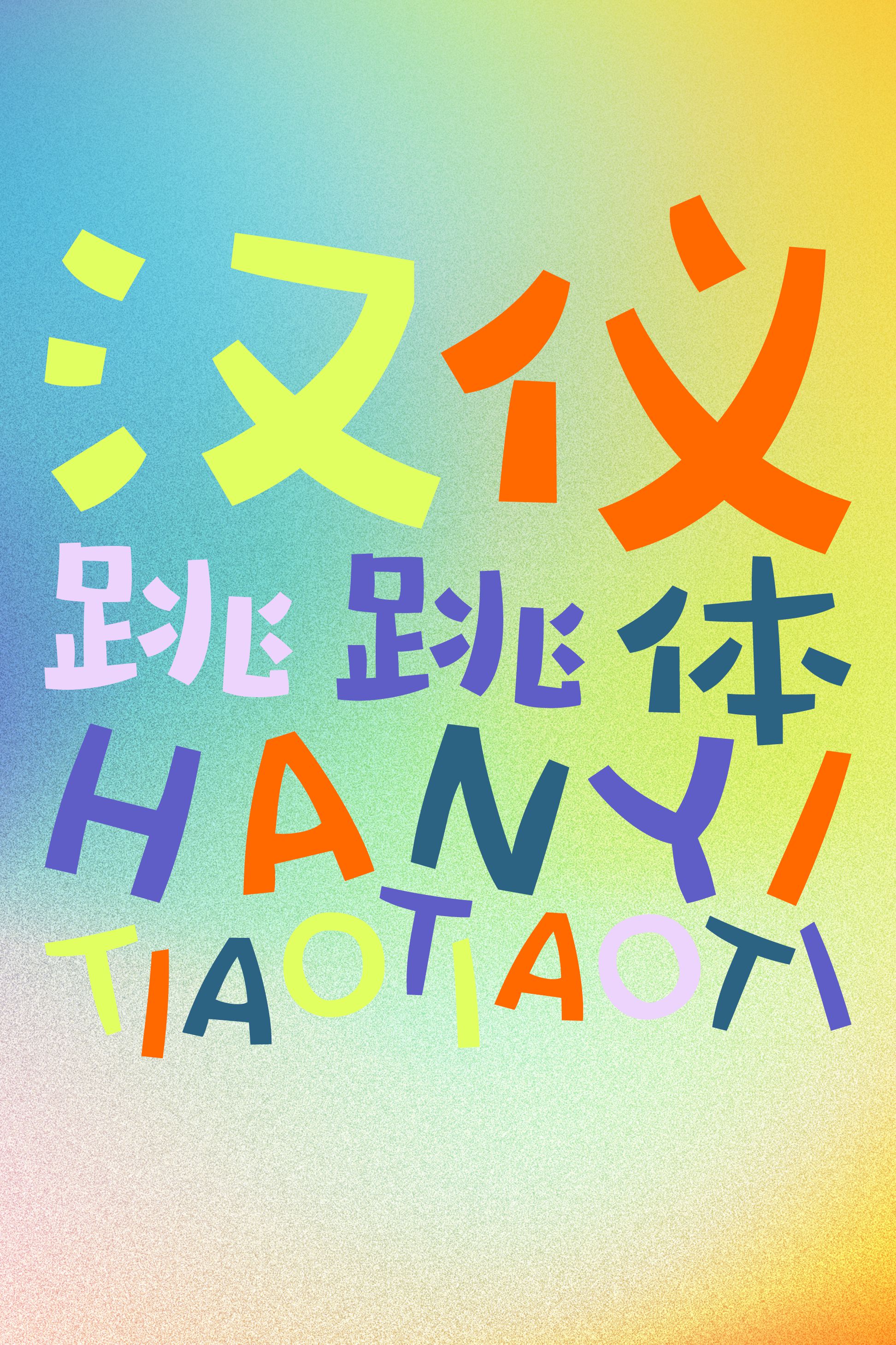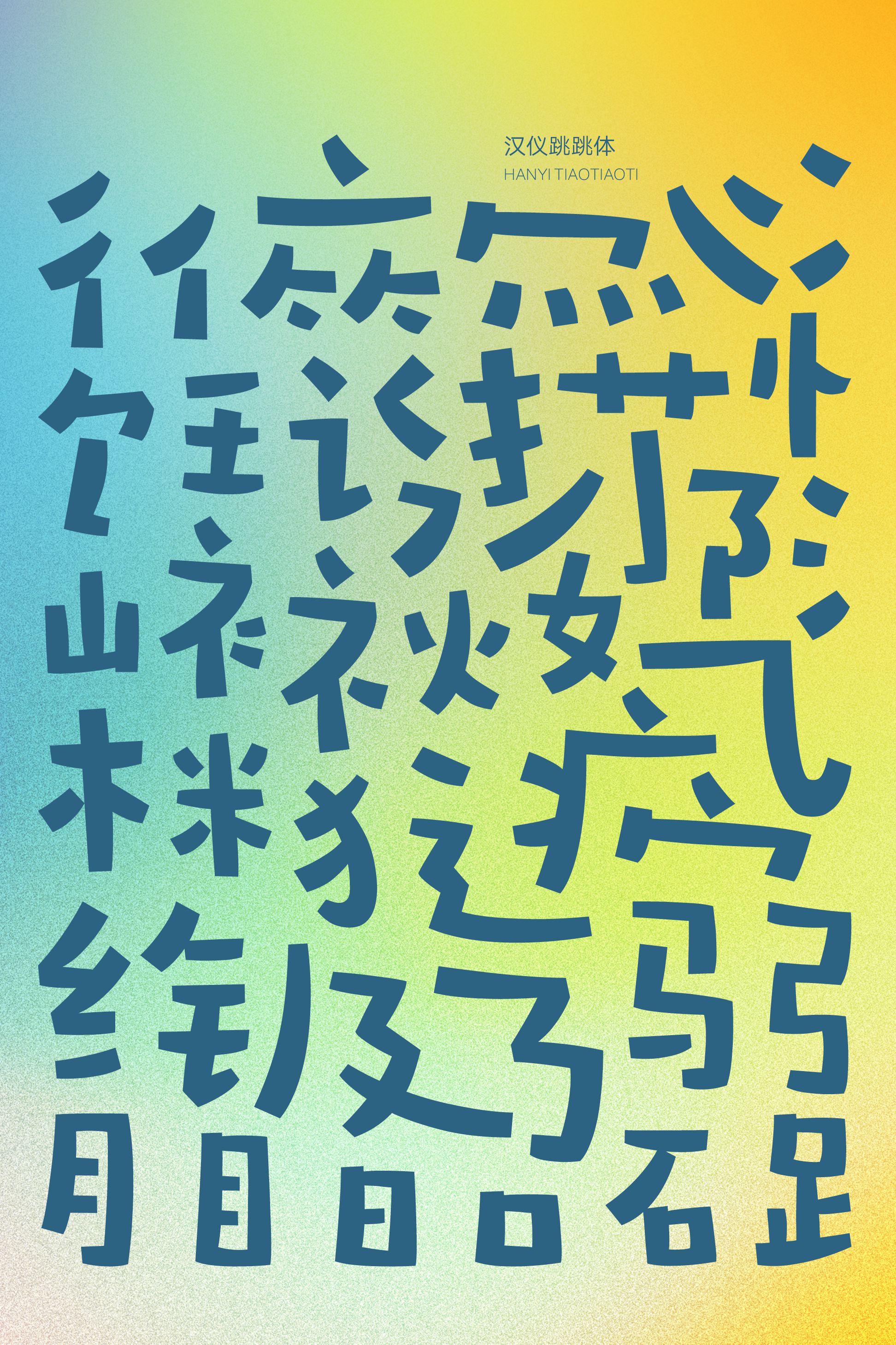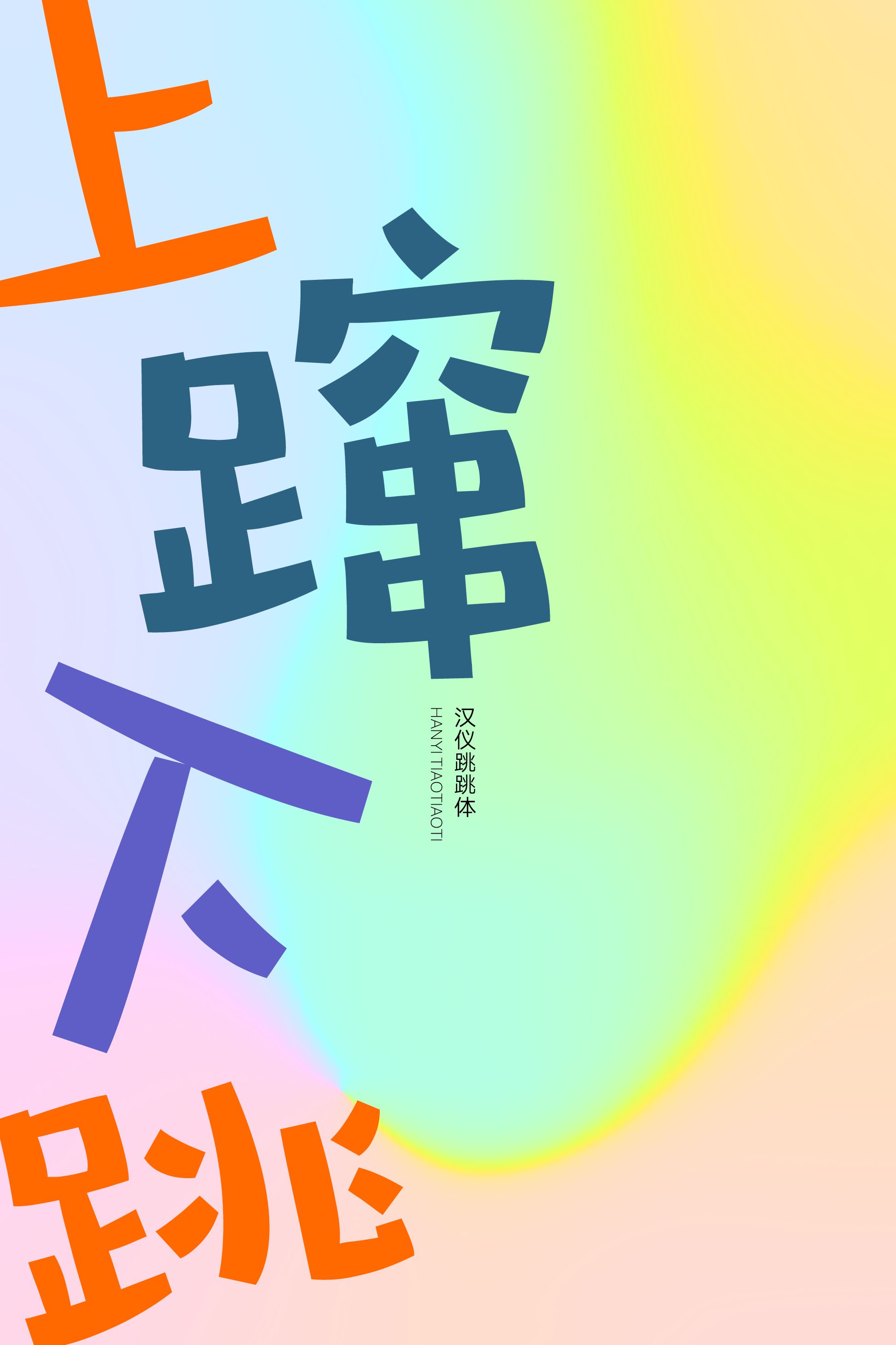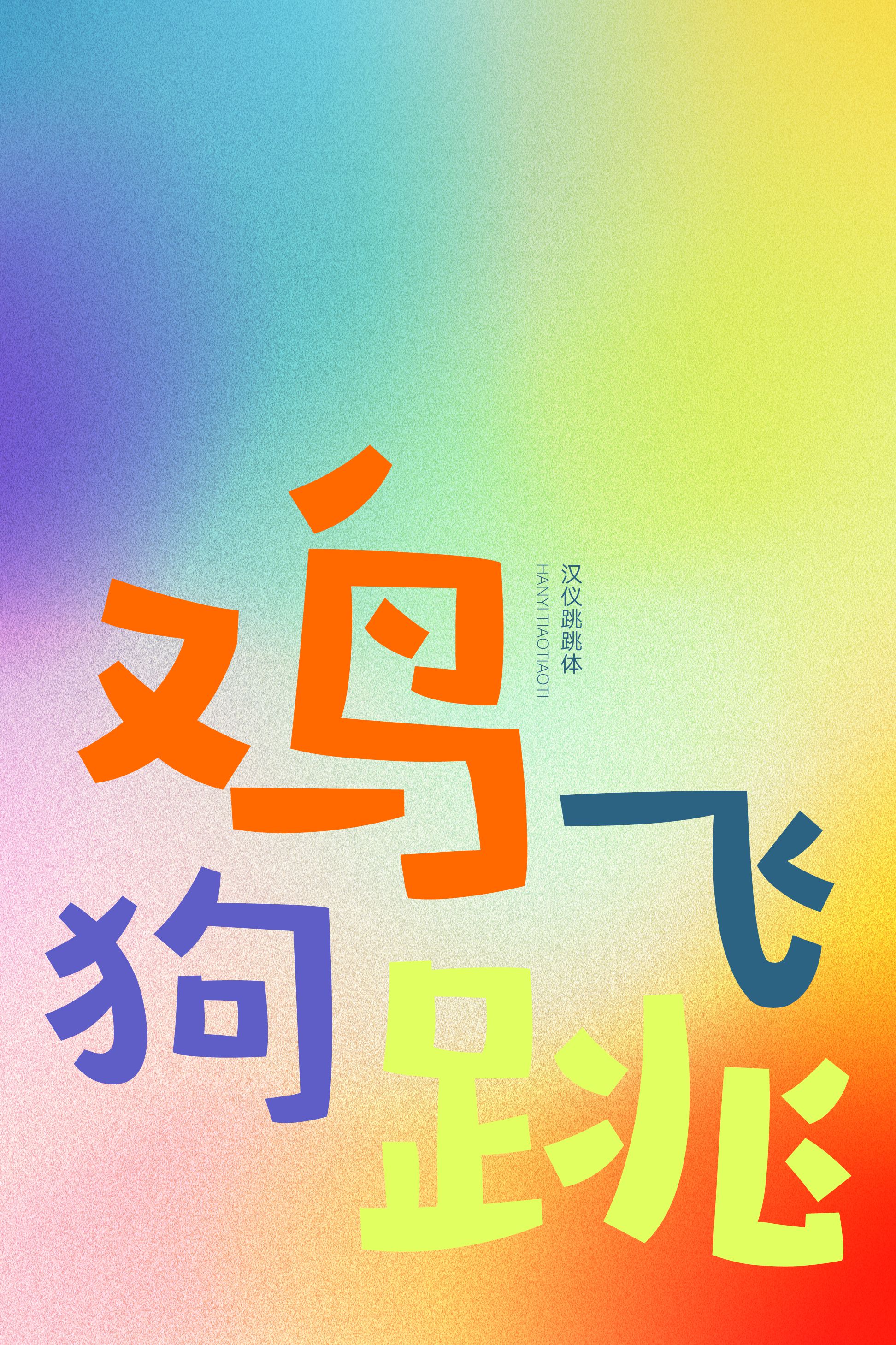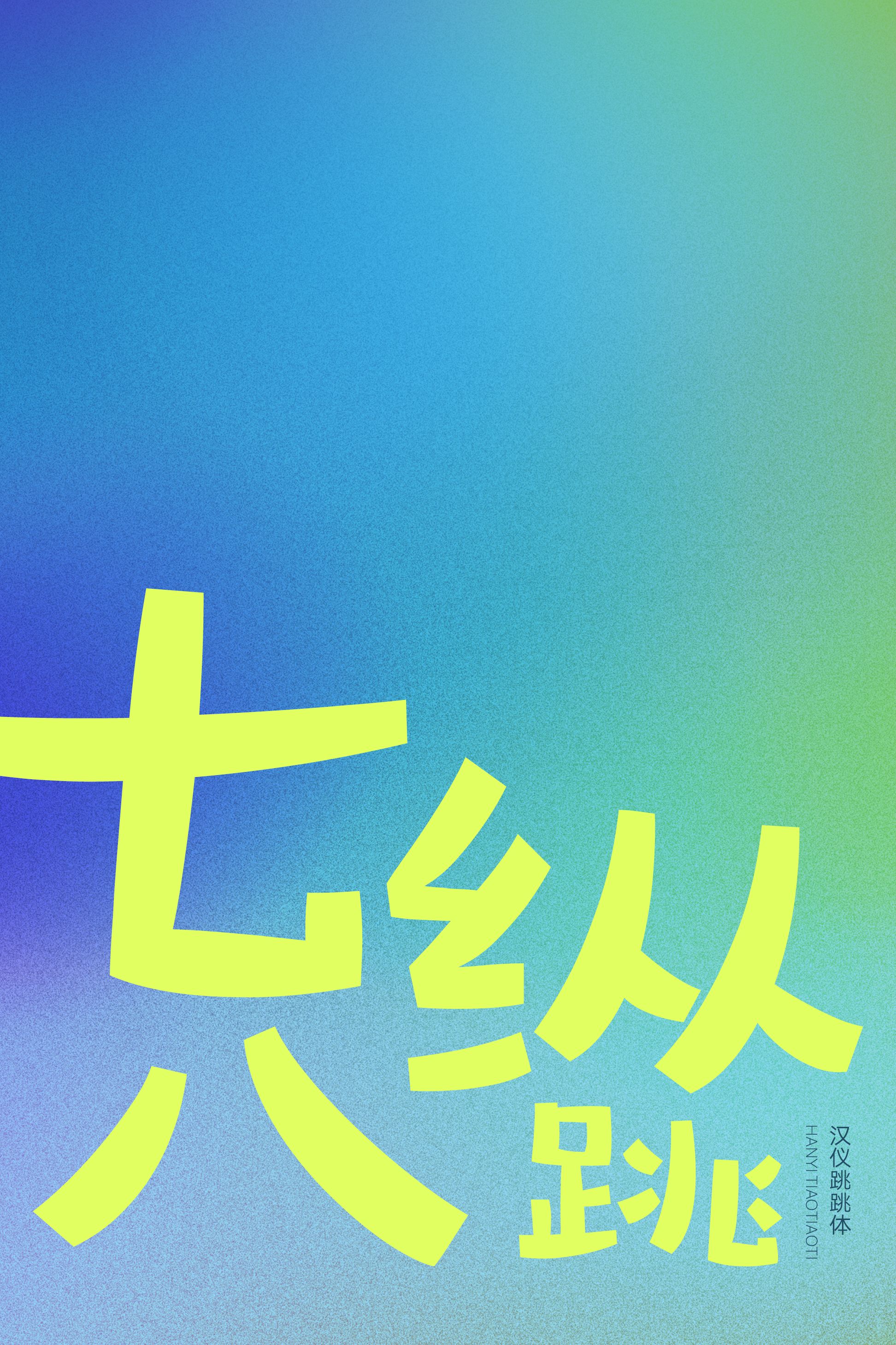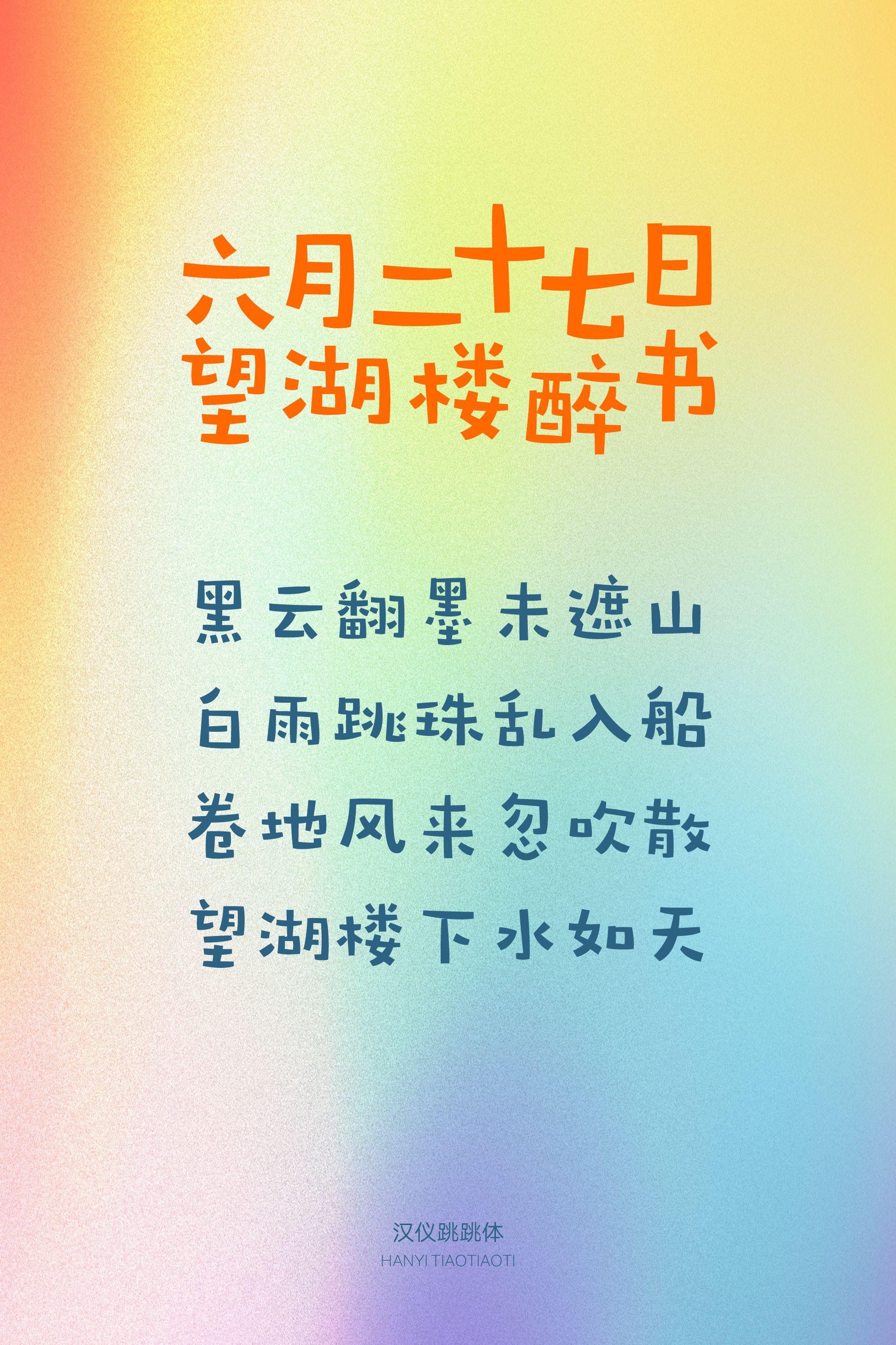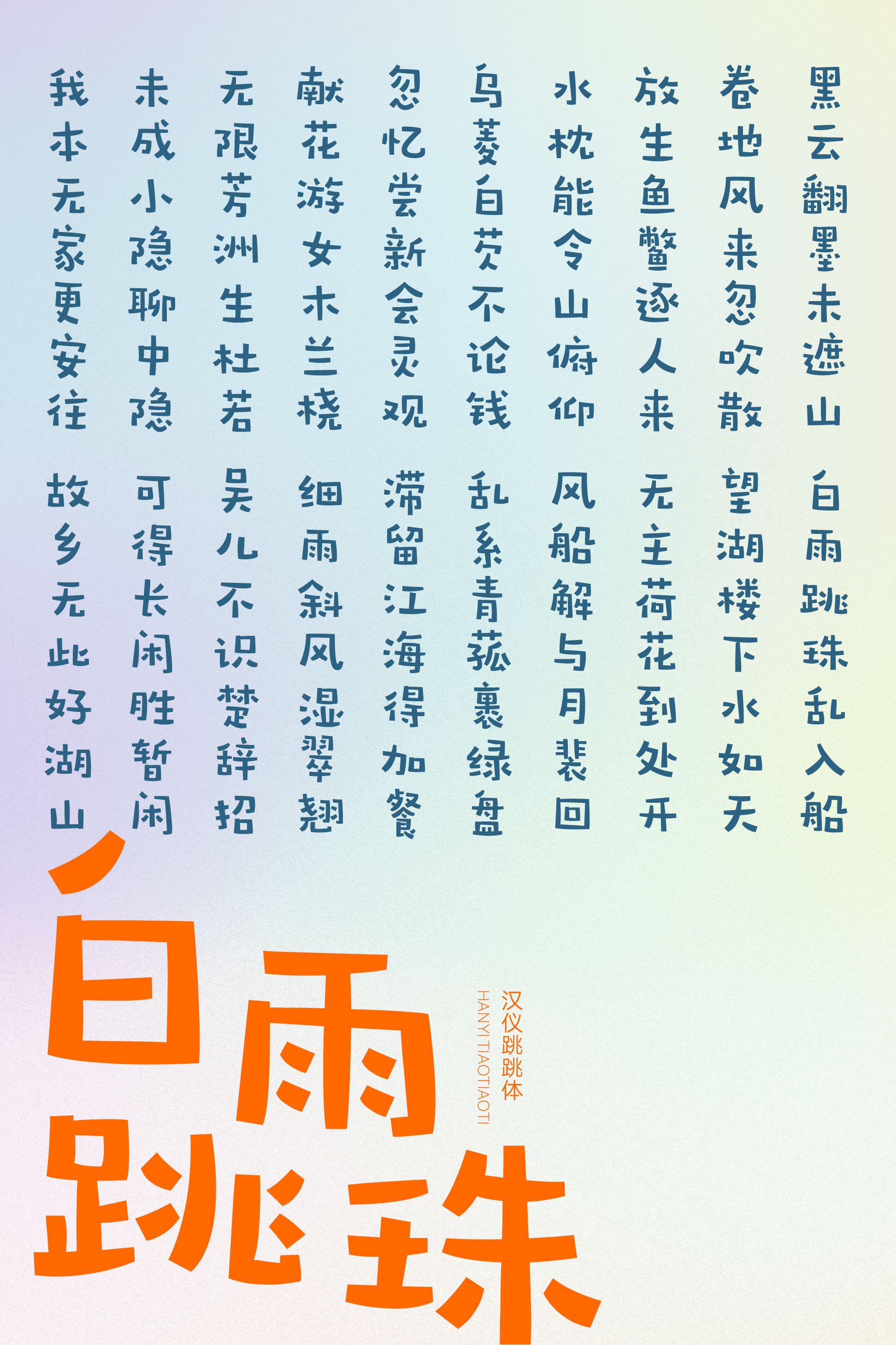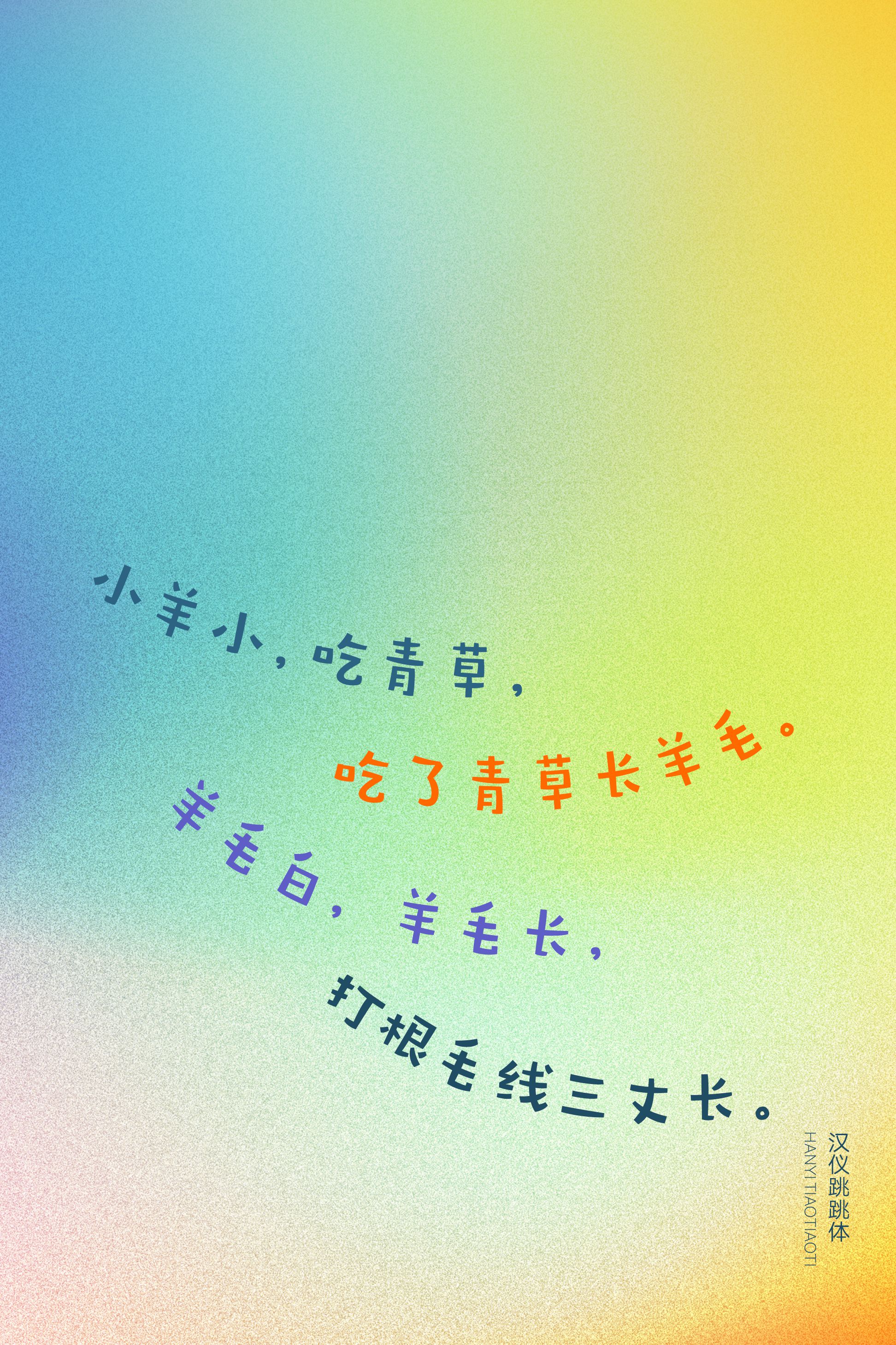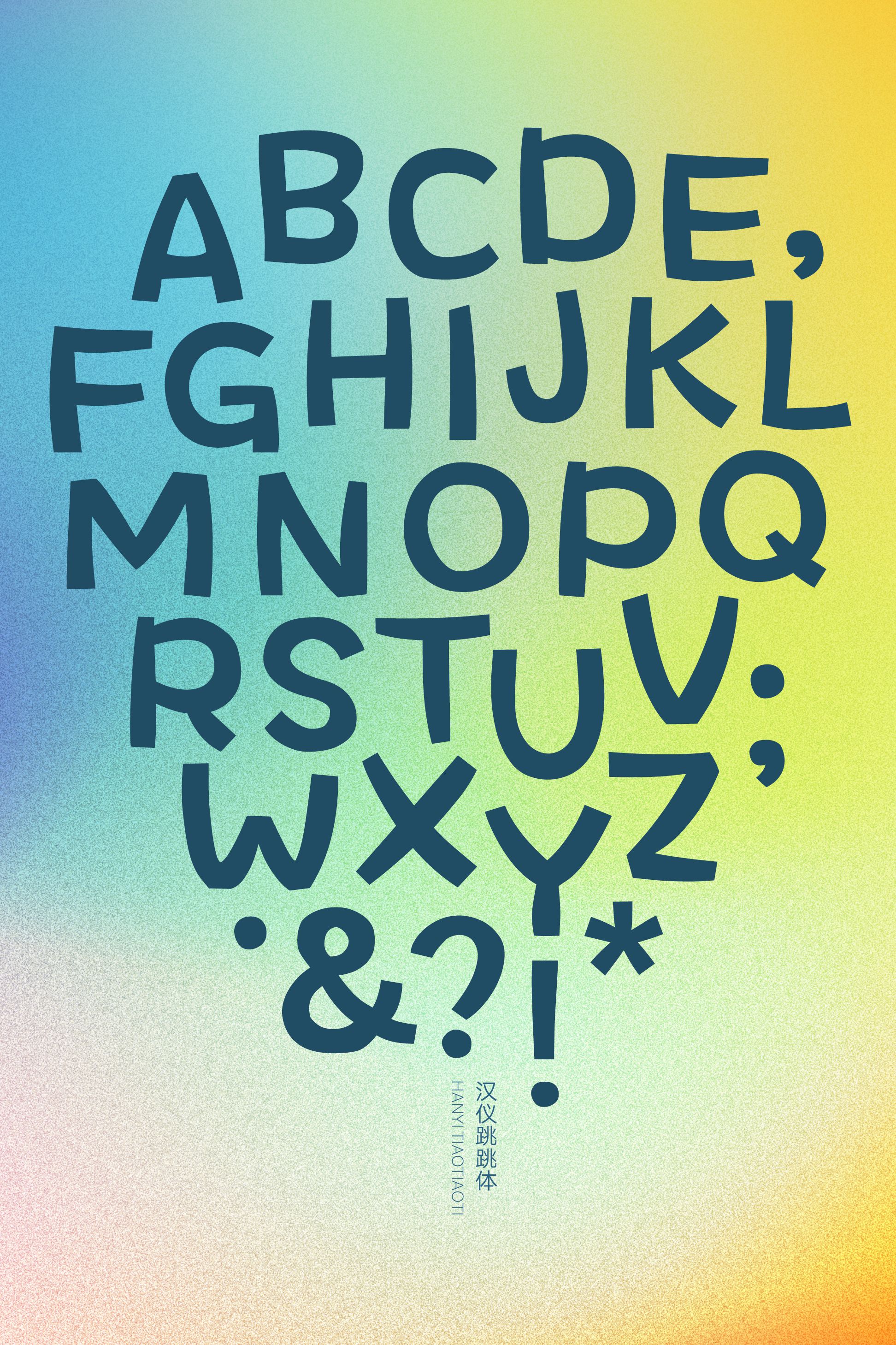
汉仪跳跳体
紧张的工作生活需要乐趣来调味,不妨从视觉入手,给劳累的双眼来一点新鲜感,放轻松。汉仪跳跳体是一款仿手写风格的美术字,被赋予了灵动的造型、俏皮的性格和丰富的形态。每一笔都独具特色,笔笔不同、字字不同,又相互映衬,抛开了那些条条框框,乐观地讲述属于自己的“故事”。
字形蹦蹦跳跳,高高低低、大大小小,乐趣无穷。
大小部件的穿插组合灵活俏皮。
方头笔画有弧度和粗细变化。
西文以相同的方笔线条构成,造型轻松可爱。